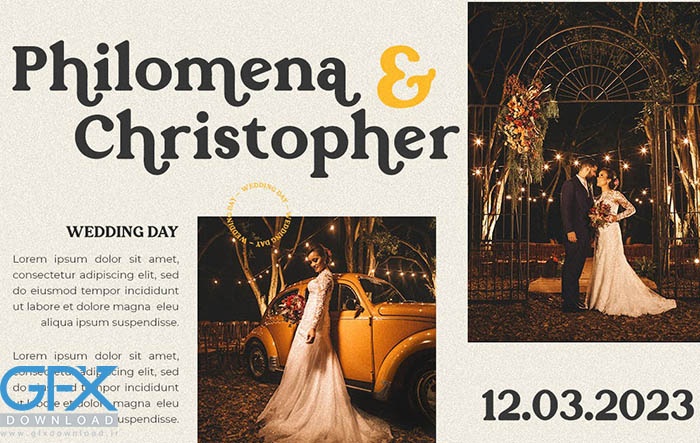
دانلود فونت Carriage
دانلود فونت انگلیسی Carriage
دانلود فونت Carriage یک فونت سریف ظریف و متمایز است. این فونت که به دلیل سبک شیک و ساده‌ای که دارد، برای طرح‌های مختلف مناسب است، بدون توجه به موقعیت، این قابلیت را دارد که به فونت مورد علاقه شما تبدیل شود!
فونت انگلیسی Carriage
دانلود فونت انگلیسی Carriage